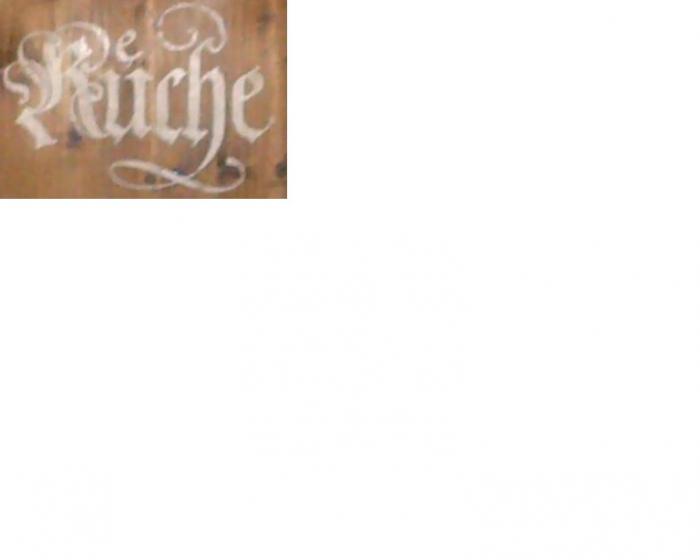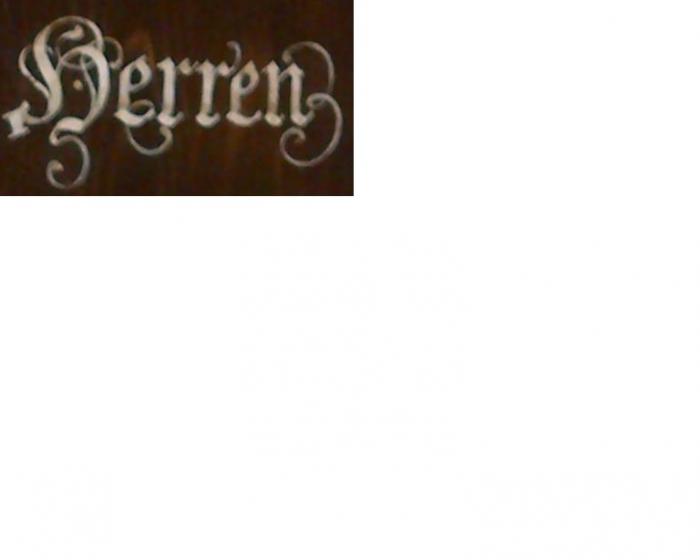
Alte schriftart Gesucht
Moin ich hab hier nen foto von einer alten schriftart in einem gasthaus. Nun stellt sich die frage welche schriftart das ist das wäre wircklich wichtig da wir in der gleichen schriftart eine neue WC tür beschriften sollen und wir absolut keine ahnung haben welche schrift das ist für hilfe wären wir sehr dankbar
alternativ würde auch eine sehr ähnliche schriftart gehen das wäre aber nur im äusersten notfall falls sich garnichts ergibt oder garkeiner auf ne idee kommt welche schriftart das ist. Einzige größere info dazu wäre das es sich um den Gasthof Schwarzer Adler in Nürnberg kraftshof handelt. dort findet man die schrift über jedem zimmer bzw. an den schon vorhandenen türen.
Nachdem das handgemalt ist, würde ich auch einen alten erfahrenen Malermeister in Betracht ziehen – der hat das nämlich noch gelernt und kann fehlende Beschriftungen im selben Stil ergänzen.
naja wir selbst sind ja die malerfirma die dort die schrift auf eine neue tür aufbringen soll. aber dazu bräuchte ich eine nähere info um welche schriftart es sich dabei wohl handeln könnte
Wie schon gesagt, ist es gar keine Schriftart, die man einfach so benutzen könnte. Dies wurde von Hand für diese eine Anwendung geschrieben.
Ihr werdet also keine Vorlagen dafür finden. Entweder braucht ihr einen kundigen Schildermaler/Kalligrafen, der anhand der Muster neue Vorlagen fertigt oder ihr werden mit einer nur ähnlichen Schrift leben müssen. Der werden dann aber z.B. die ganzen Verschnörkelungen fehlen, die passend für die konkrete Anwendung angebracht wurden.
Wenn’s die Authentizität und Qualität des Originals haben soll, kommt man um eine – ich sach mal – Kommissionierung nicht umhin. Wenn über allen Zimmern sowas zu finden ist, sollte man doch alle Buchstaben, die man braucht irgendwo finden, oder?! Selbst wenn es eine Schrift gäbe, die sehr ähnlich ist, wird das anders aussehen und besser passen, wenn man diese noch etwas anpasst. Wenn’s gut sein soll ist es eben aufwendig ...
Das sollte doch aber auch ohne Font zu machen sein, mit den Vorlagen, denke ich  :nicken:
Und ob man stundenlang nach einem passenden Font sucht oder die Zeit in Skizzen und Zeichnungen investiert, kommt doch am Ende (auf der Rechnung) auf’s gleiche hinaus  :tuschel:
naja wir selbst sind ja die malerfirma die dort die schrift auf eine neue tür aufbringen soll. aber dazu bräuchte ich eine nähere info um welche schriftart es sich dabei wohl handeln könnte
ah, ok. Norbert hat ja inspirierende Vorschläge gemacht, das ist für die Orientierung schon gut. Wenn du in deinen beiden Beispielen das "e" vergleichst, siehst du, dass das formal voneinander abweicht. In Details zwar, aber es weicht ab. Unterschiede hab ich dir grün gekennzeichnet:
Ich würde mich für eine der beiden Varianten entscheiden (als nicht-kalligraphisch Begabter für die einfachere …  :-| ) und in diesem Stil weitermachen.
… dazu bräuchte ich eine nähere info um welche schriftart es sich dabei wohl handeln könnte
Es handelt sich um eine handgeschriebene Fraktur, das sieht man doch wohl eindeutig. Und das ist auch sämtliche Information, die man braucht. Es gibt gelernte Schrift- und Graphikmaler (ja, der Beruf hieß wirklich so!), die haben es drauf, aus fünf vorhandenen Buchstaben das komplette Alphabet abzuleiten und auch die Zierelemente bei einer Neubeschriftung adäquat nachzuempfinden.
Wenn man’s nicht selbst kann, sucht man sich jemanden der es kann. Ganz einfach.
Oder man bildet sich weiter, wenn man vom Fach ist. ;-)
Das macht man aber nicht mal so eben für einen Job  ;-)
So ein bisschen Grundkenntnisse sollte man da schon haben, das ist dann aber, denke ich, kein so großes Problem. Man hat ja doch einigen Spielraum beim ausgestalten der Buchstaben, wie bertel dargelegt hat.
Oder man bildet sich weiter, wenn man vom Fach ist. ;-)
Was ist denn "das Fach"? Du bist aus dem graphischen Gewerbe – kannst du perfekt html5 programmieren, 4D-Animationen erstellen oder perfekte Ergebnisse mit der Breitfeder abliefern, nur weil du "aus dem Fach" bist? Ich persönlich finde diese Einstellung ein klein wenig überheblich.
Von Hand aufgebrachte Schriften sind für einen Malermeister schon lange kein alltäglicher Job mehr, und selbst damals™ haben das spezialisierte Schrift- und Graphikmaler ausgeübt.
Edit: Allein die Tatsache, dass ein Malermeister, der per se mit Typographie erst mal nix zu tun hat, ein so krudes Fachforum wie das unsrige überhaupt findet, zollt mir Respekt ab, jeder andere hätte einfach irgendwas hingemalt. Da sind dann selbst spanische Kirchen nicht vor Dilettanten verschont …
@bertel
Bitte mal ganz ruhig. Warum ist es überheblich wenn ich dem Fragesteller erstmal positiv unterstelle, dass er das womöglich drauf hat? Wenn er damit beauftragt wurde, geschieht das ja vielleicht nicht ohne Grund und er war schlicht und ergreifend einfach nur auf der Suche nach einem passenden Alphabet so wie das damals in dem von mir verlinkten Projekt von uns auch der Fall war – wo ich mir im übrigen selber nicht zugetraut habe die Fraktur an die Wand zu bringen, auch wenn das ein Bestandteil meiner Ausbildung war. Und warum gleich Geschütze wie html5 und 4D-Animation? Ich wüsste nicht warum ich das zum grafischen Gewerbe zählen sollte, dafür gibt es auch bei uns eigene Abteilungen mit entsprechenden Spezialisten.
Das erinnert mich an Werbetechniker und Typografie. Bei der Montage von Buchstaben kann was schief gehen. Wenn dann der Werbetechniker solide bis gute Kenntnisse in Typografie hat, so kann dieser Fehler bei der Montage vermeiden oder korrigieren. Oder wenigstens eine Rückmeldung geben. In 99% aller Fällen ist das unerheblich, aber das eine % kann peinlich und teuer werden. Das ist zwar nicht direkt vergleichbar, zeigt aber den Wert des Wissens an für sich auf.